今回は、ひと目で異様さが伝わるような「毒々しい雰囲気」のある日本語フリーフォントをご紹介します。
不穏さや狂気、妖しさ、禍々しさなどそんなネガティブだけど強烈なインパクトを持つフォントは、ホラーやサイコ系のデザイン、退廃的な世界観、ヴィレヴァン的サブカル表現にぴったりです。
見る人に違和感や緊張感を与える個性的なデザインは、使い方次第で唯一無二の世界観を演出できます。
今回は、どこか危うく、不気味でクセの強い、毒気を帯びた日本語フリーフォントをピックアップしてみましたので、刺激的な表現にぜひ取り入れてみてください。
「毒々しい雰囲気」のおすすめフォントまとめ
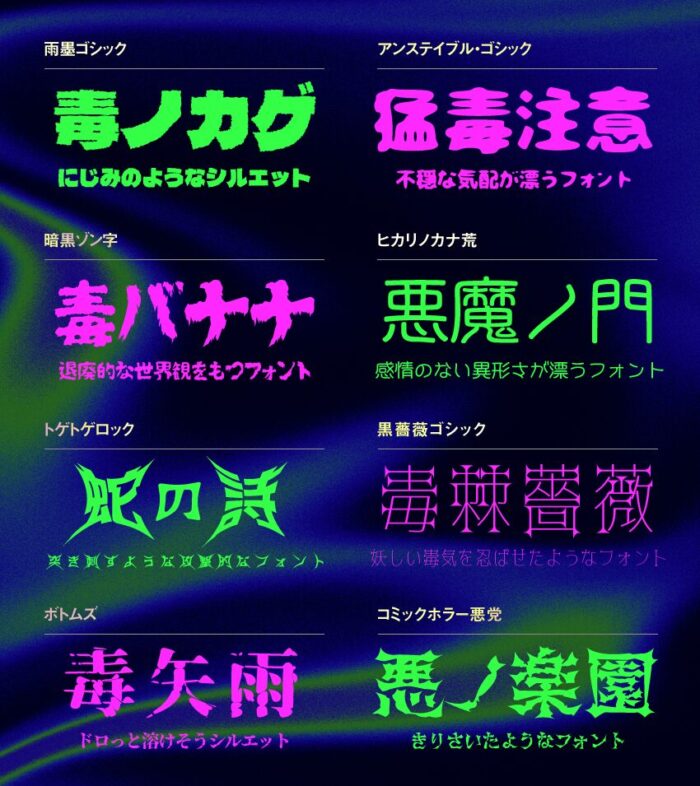
アンステイブル・ゴシック
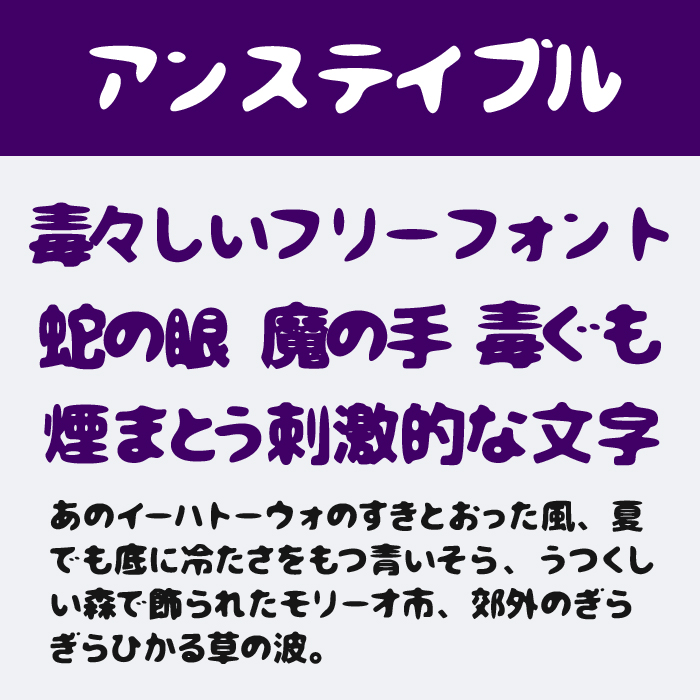
アンステイブルフォントは、ふにゃりとした輪郭のゆらぎが特徴で、可愛さの裏に不穏な気配がただよう不安定さのあるフォントです。
雨墨ゴシックフォント
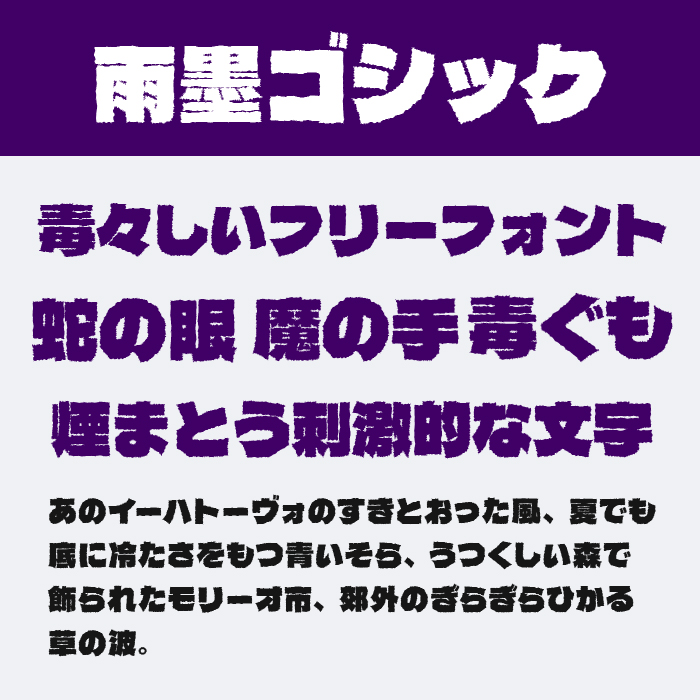
雨墨ゴシックフォントは、墨のようなにじみと筆跡の荒々しさが混ざり合い、濡れたような不気味さをもつ重厚なフォントです。
テンドゥ
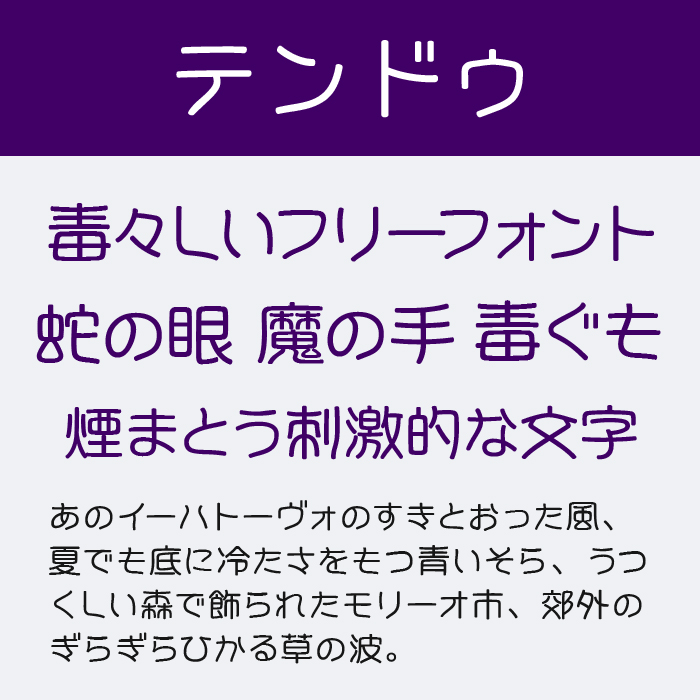
テンドウフォントは、丸みのある繊細なラインで無機質な静けさを描き出す、感情のない異形さが漂う篆書体のようなフォルムが素敵なフォントです。
黒薔薇ゴシック
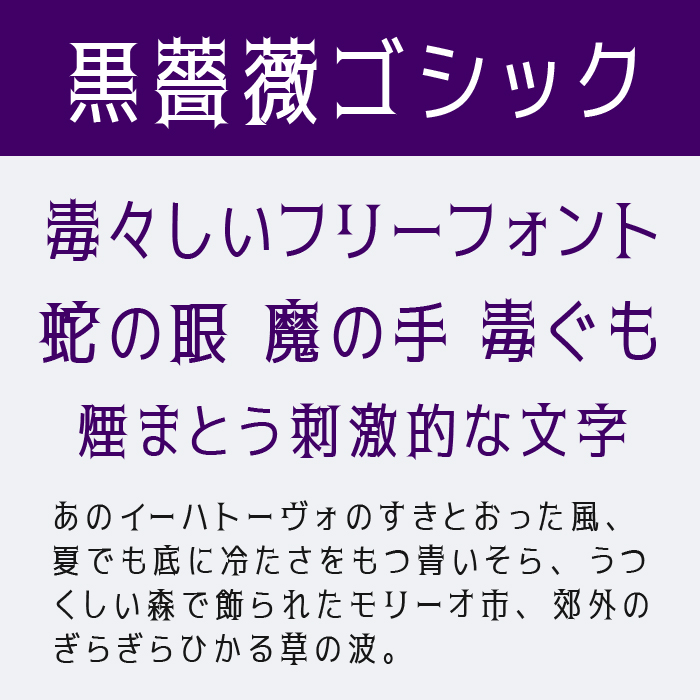
黒薔薇ゴシックフォントは、整った骨格に妖しい毒気を忍ばせたような、上品さと危うさが共存するダークロマンなフォントです。ウェイトも7種類用意されており、太さによって印象が変わるユニークなフォントです。
トゲトゲロック
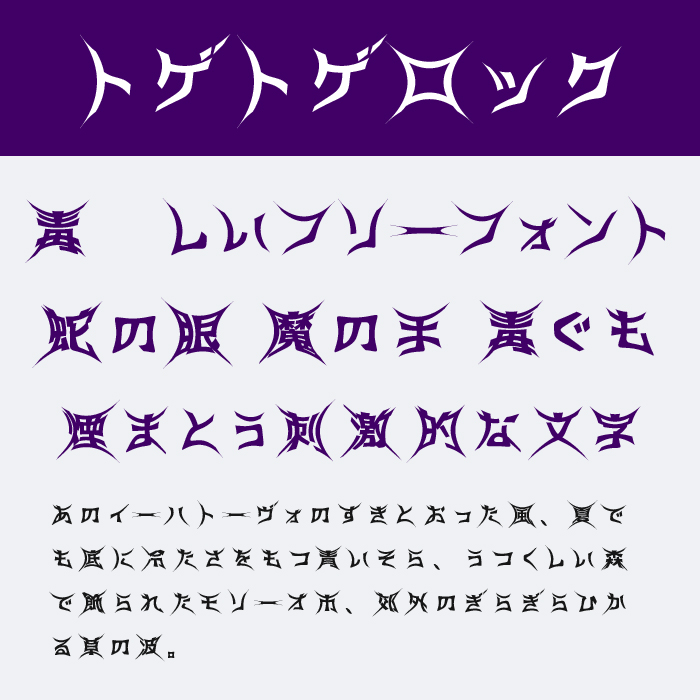
トゲトゲロックフォントは、鋭い角と極端なとがりが印象的で、冷たく突き刺すような緊張感をまとった攻撃的なフォントです。使い方によっては「可愛く」「ロック」「ハード」など、さまざまな印象に使い分けることができるフォントです。
源界明朝
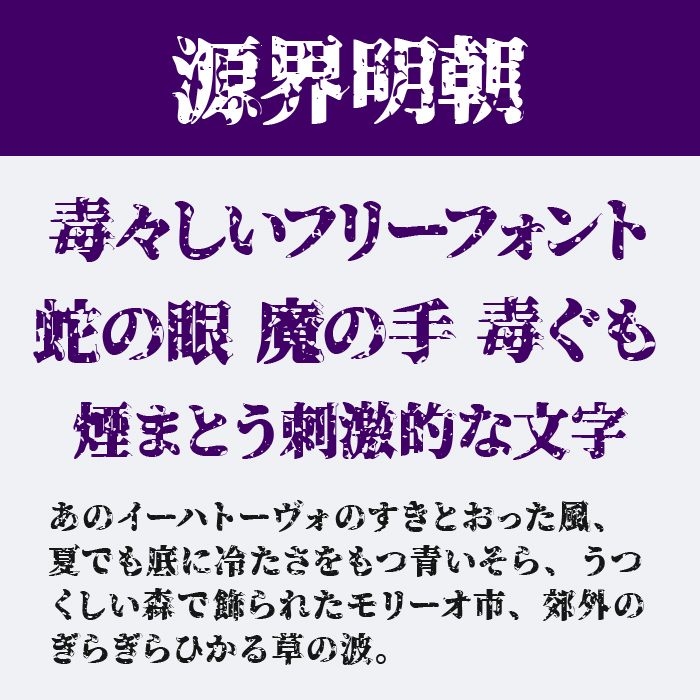
源界明朝フォントは、崩れかけた明朝体に異界的なノイズを重ねたような、退廃と幻想が混ざり合う独特な質感をもつデザインフォントです。
暗黒ゾン字
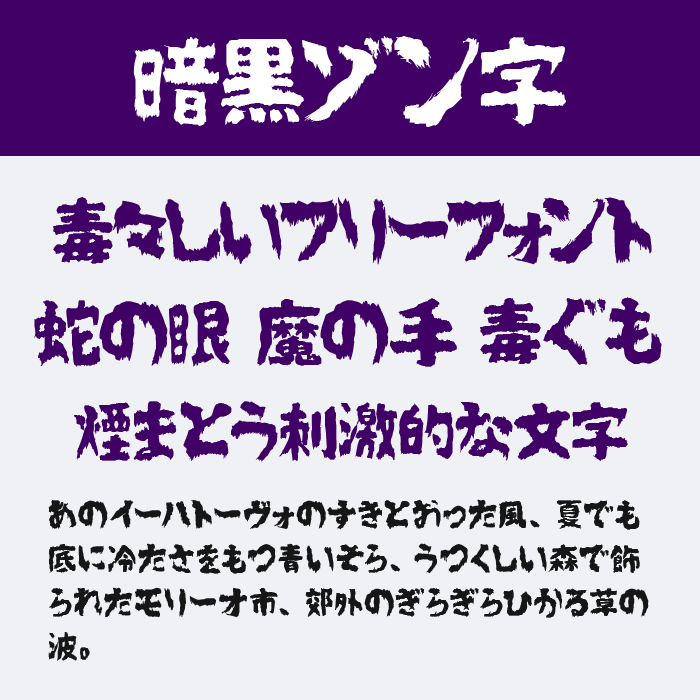
暗黒ゾン字フォントは、お化け屋敷の看板文字として制作されているフォントですが、にじんだ筆跡とゆがみが腐敗した感覚を呼び起こす、ゾンビ的で退廃的な世界観をもつフォントです。
コミックホラー悪党
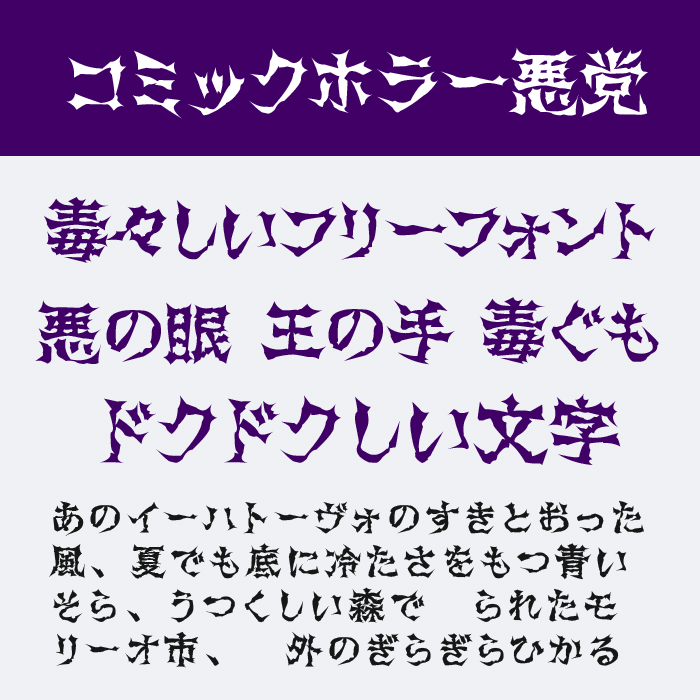
コミックホラー悪党フォントは、鋭利な切り裂き模様が随所にちりばめられ、紙を裂いたような不穏で劇画的な雰囲気のフォントです。
ボトムズG
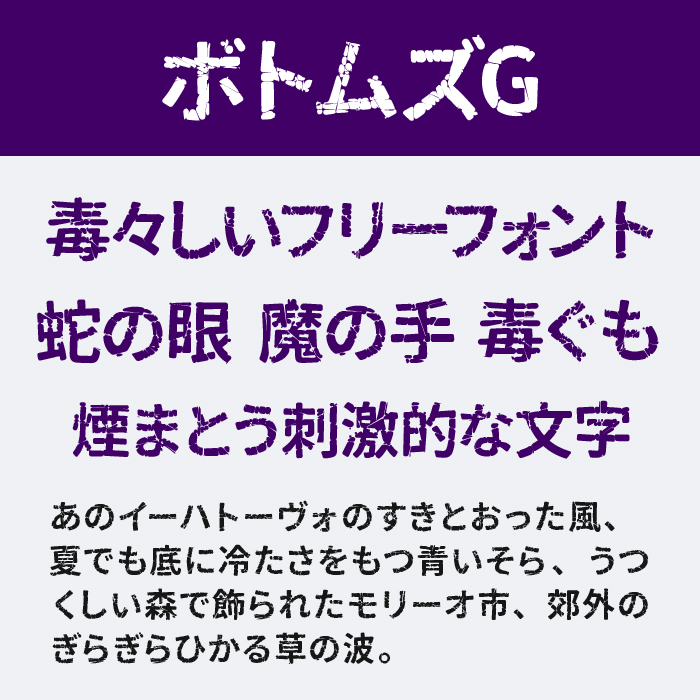
ボトムズGフォントは、擦れた質感と不均一なアウトラインが混沌とした狂気を想起させる、異形の存在感が強いフォントです。